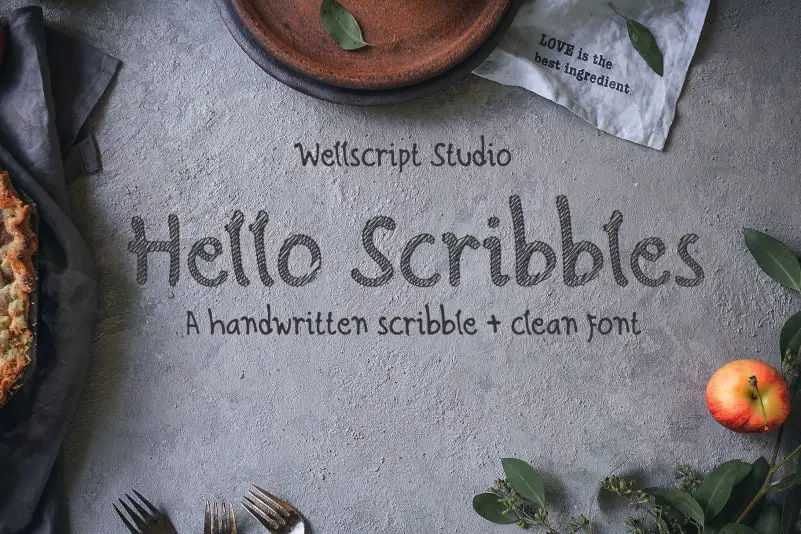
Hello Scribbles – Handwritten font – Fonte Grátis
Hello Scribbles - Handwritten font
Hello Scribbles é uma fonte de escrita manuscrita original que oferece um toque único e descontraído com suas traçagens de desenhos. Perfeita para designers, artistas, criadores de conteúdo de cartun ou até mesmo amantes do design gráfico, essa fonte vem como um complemento perfeito para qualquer projeto. Seja para personalizar uma carta de aniversário, criar materiais escolares em papel, ou adicionar um toque pessoal a um livro, Hello Scribbles é versátil e capaz de se adaptar à uma variedade de aplicativos criativos. Ideal para quem deseja inovar com uma escrita manuscrita que transmite lealdade e individualidade, essa fonte captura os momentos mais importantes da vida através de suas linhas curvas e desenhos. Ideal tanto para um projeto digital quanto para impressão, a Hello Scribbles vem com uma vasta gama de opções coloridas que se tornam ideais para personalizar textos de forma única. Seja criando materiais escolares animados ou decorando seus cadernos e livros com um toque pessoal, você encontrará em Hello Scribbles o recurso perfeito para adicionar uma dose extra de originalidade aos seus projetos.